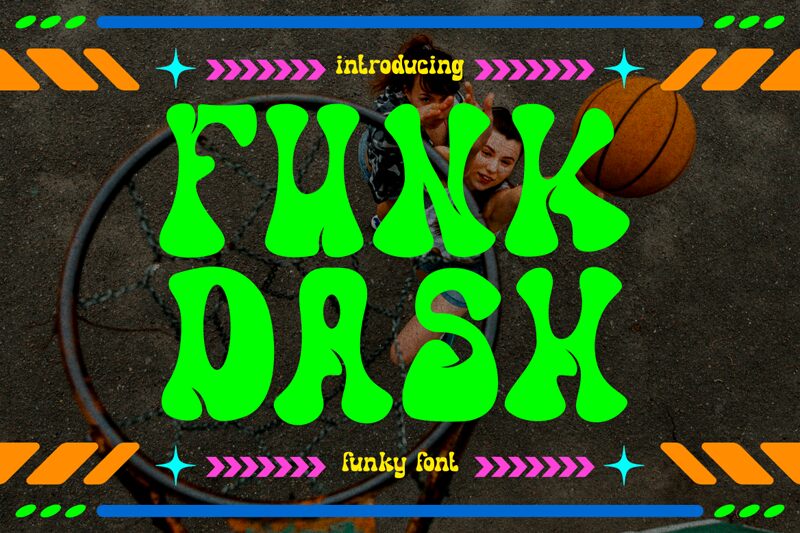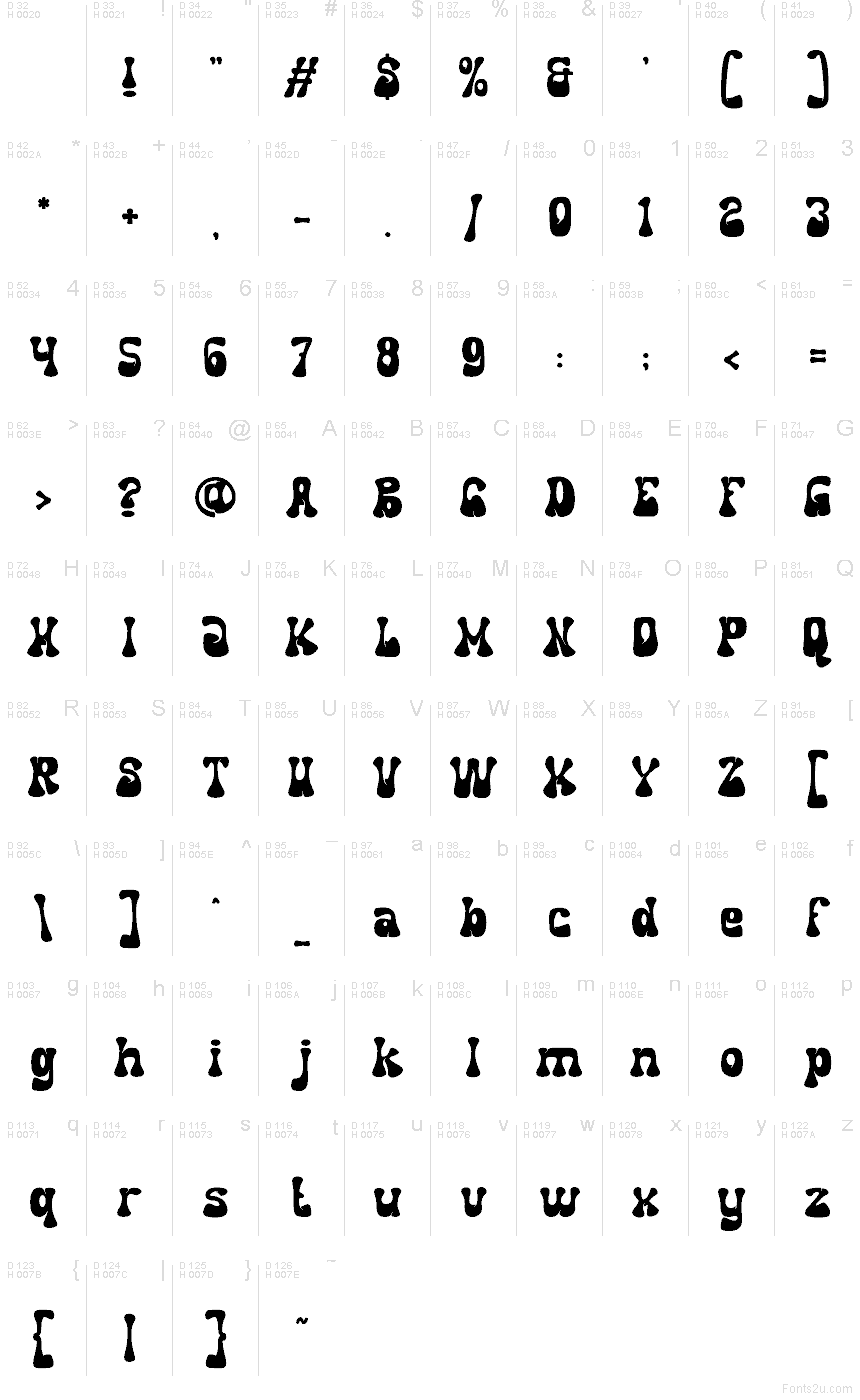
Funkdash
Shanaf Studioが手がける「Funkdash」は、70年代のサイケデリックなムードを漂わせる、グルーヴィーで無料のディスプレイフォントです。角の取れたふっくらとしたインク溜まりのような形状が特徴で、幾何学的なカッチリした雰囲気とは対照的に、ソフトで波打つようなゆったりとした印象を与えます。ポスター、音楽パッケージ、フェスティバルのブランディング、カフェのメニュー、雑誌の表紙、タイトルロゴなど、レトロなポップカルチャー感を即座に出したい場面に最適です。その塊のようなうねるフォルムを活かすため、見出しやロゴタイプなど、文字のリズムを際立たせる短いフレーズでの使用をおすすめします。